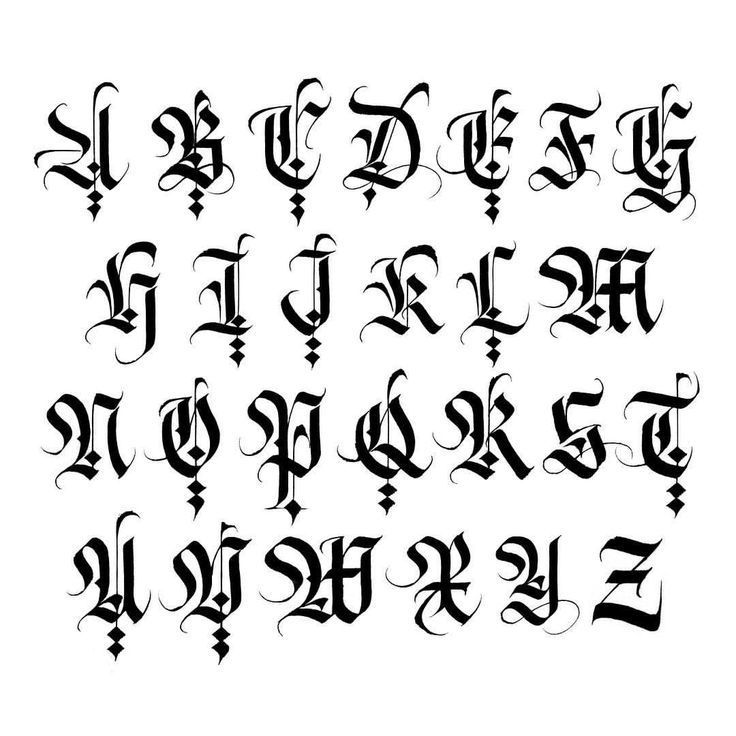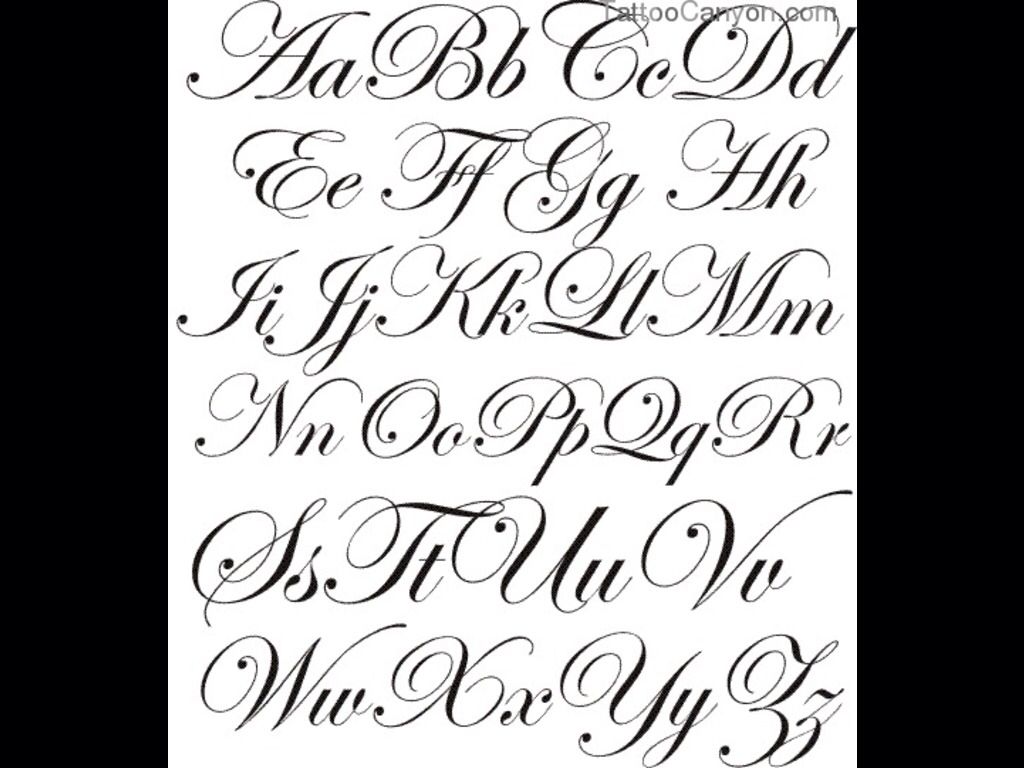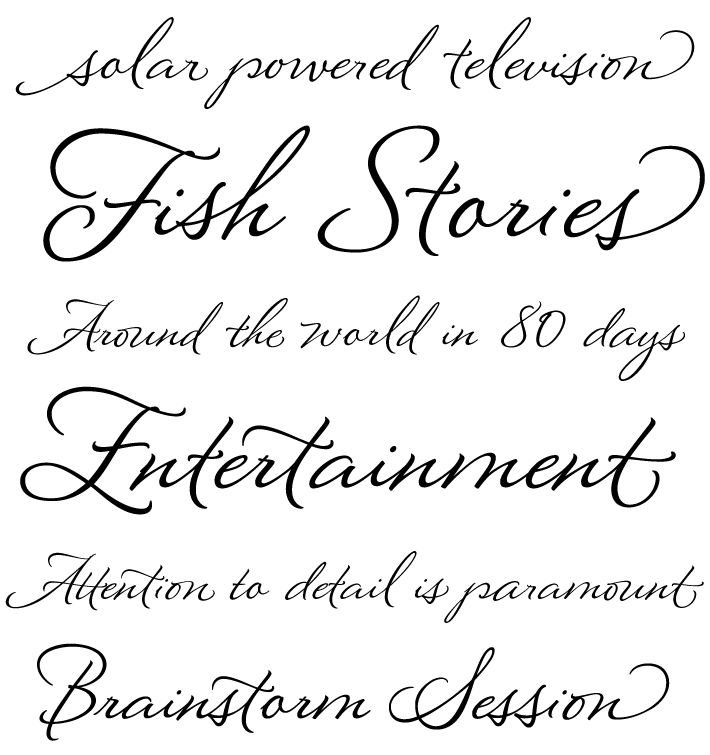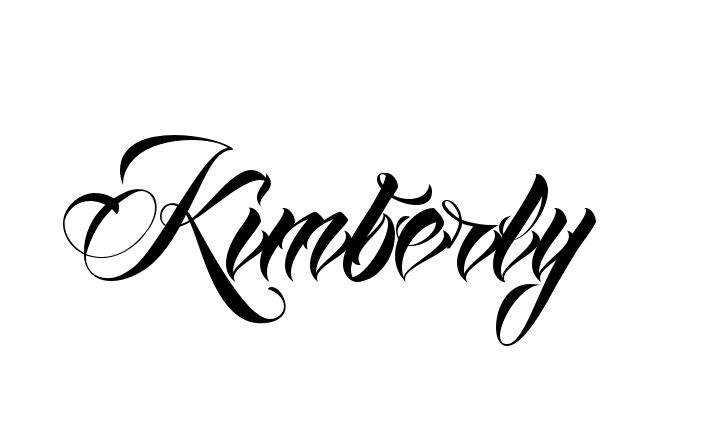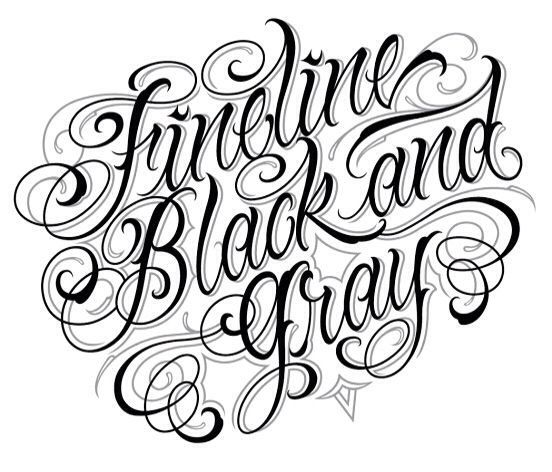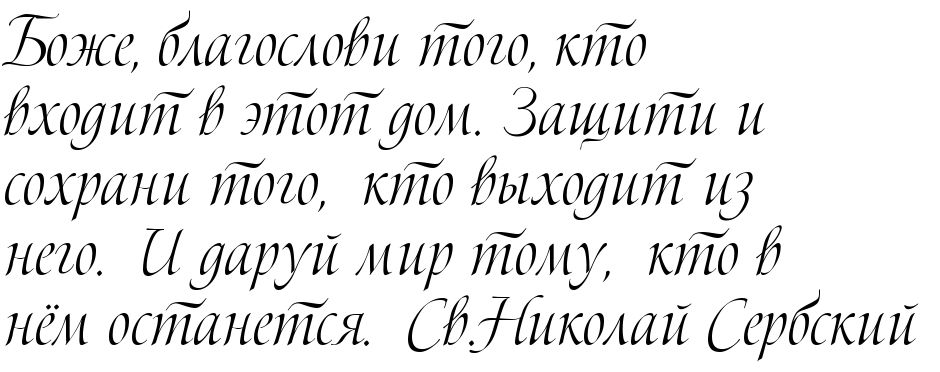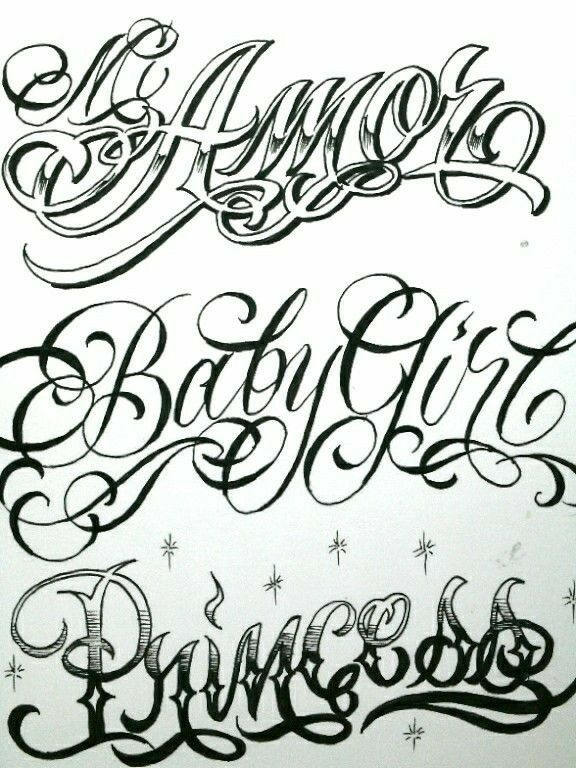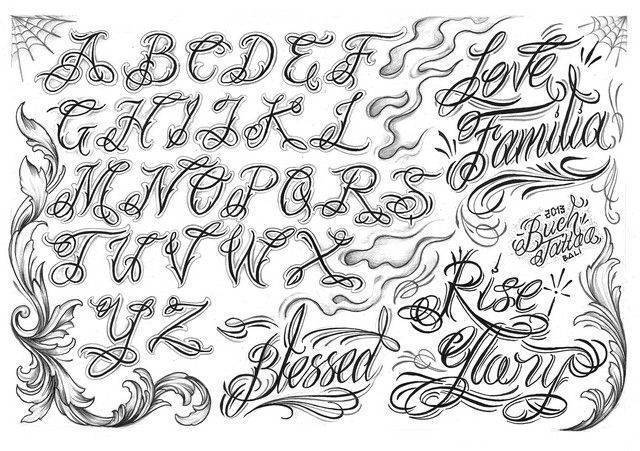
Шрифт тату онлайн: Шрифты для тату онлайн — подбери красивую фразу для татуировоки.
виды шрифтов. Западный шрифт на теле у девушки
Для тех, кто решил нанести на тело татуировку, наиболее серьезной проблемой является выбор рисунка или надписи. Ведь трудно создать тату надпись
так, чтобы не пожалеть об этом в течение всей жизни. Трудно однако очень даже возможно, для этого изначально следует рассмотреть абсолютно все варианты, взвесить преимущества и недостатки, а также понять, что именно вы хотите видеть на себе каждый день.
Во многих случаях, когда человек вроде бы уже определился с выбором надписи, проблемой становится тату шрифт, которым будет сделана татуировка.
Для того, чтобы смысл надписи совпадал бы со стилем, следует понять, что одна черточку, наклон буквы или размер слова может повлиять на восприятие смысла.
Если для татуировки вы выбрали длинную надпись или даже целое предложение, то советуем подобрать более компактные виды шрифтов, буквы в котором наносятся без наклона или же с небольшим наклоном.
Неважно, присматриваете ли вы себе татуировку впервые или вы — тату-сноб, выбор правильного шрифта требует терпения. Поэтому сегодня мы представим вам 50 сумасшедше прекрасных шрифтов, которые вам обязательно понравятся.
С подборкой шрифтов по рекомендациям GraphicRiver и Envato Elements, эта коллекция включает в себя 50 прекрасных шрифтов, которые вам определённо захочется внедрить в свою следующую работу.
50 сумасшедше невероятных шрифтов для тату
Вам нравится дизайн татуировок? Нам — определённо! От диких декоративных шрифтов до великолепных рукописных шрифтов — у нас есть всё, что может вам понадобиться.
Насладитесь этой разнородной коллекцией, представленной ниже, и напишите в комментариях, что вам понравилось больше!
Рукописный шрифт
Нельзя иначе представить начало этой коллекции кроме как представлением удивительного шрифта. Этот рукописный шрифт был создан на основе завитков традиционных татуировок и уникального стиля написания «от руки». В этом начертании слились воедино полный комплект заглавных и маленьких букв, цифр и бонусный набор границ для удобства.
Шрифт «Тату Капитана Кука»
Назван в честь знаменитого Капитана Джеймса Кука, который случайно наткнулся на удивительных татуированных людей в Южной части Тихого океана.
Этот шрифт сочетает крутой декоративный стиль, идеальный для моряка или пирата. Его рекомендуемый размер для прекрасного дизайна вашего следующего тату-проекта — 36 точек или больше.
Шрифт Aseina
Если вам нужен уникальный стиль с традиционным винтажным колоритом, попробуйте шрифт Aseina. Этот шрифт создаёт ощущение красивой элегантности из-за идеального сочетания букв, цифр и глифов в этом единственном в своём роде винтажном стиле.
Шрифт Conchita
Созданный на основе тату-шрифтов, этот шрифт из заглавных букв выполнен в дерзком стиле, который заметен сразу. Скачайте этот набор для получения доступа к полной коллекции заглавных букв, цифр и знаков препинания.
Шрифт BloodOnMyBlade
Любители татуировок, будьте осторожны. Этот шрифт в два счёта превратит вас в хулиганов. Созданный на основе стиля татуировок западного побережья, этот шрифт имеет агрессивный готический дизай. В этот сет входит полный набор букв, цифр и знаков препинания.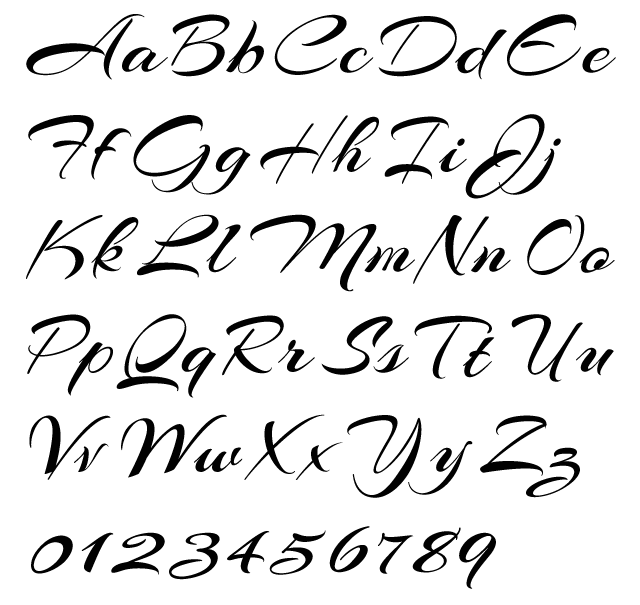